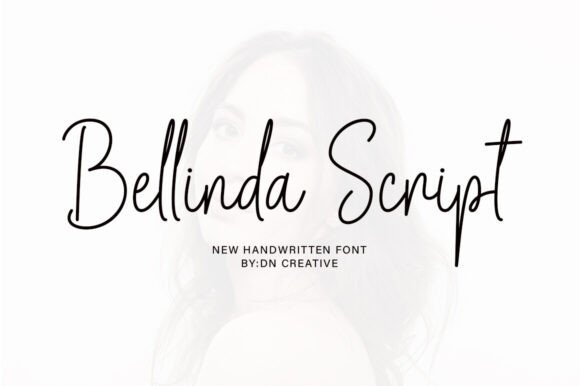
Bellinda Script
Encontrar os elementos de design certos pode ser um desafio, mas Bellinda Script oferece uma coleção excepcional que eleva o seu trabalho instantaneamente.
Trabalhado com precisão, Bellinda Script fornece vetores limpos, tipografia suave e uma licença comercial para sua tranquilidade.